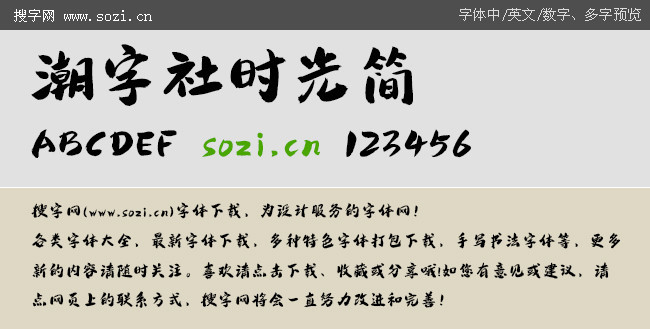
潮字社時(shí)光簡
搜字網(wǎng)提供一款潮字社時(shí)光簡中文字體下載,潮字社時(shí)光體剛毅中又平添柔和,整體方正飽滿,視覺沖擊力強(qiáng),力量感突出,節(jié)奏分明,充滿藝術(shù)張力,適用于書籍封面設(shè)計(jì)、報(bào)刊標(biāo)頭設(shè)計(jì),包裝設(shè)計(jì),海報(bào)設(shè)計(jì)等廣告應(yīng)用。(此款為個(gè)人非商用版,如需商用請(qǐng)聯(lián)系銳字工房購買)